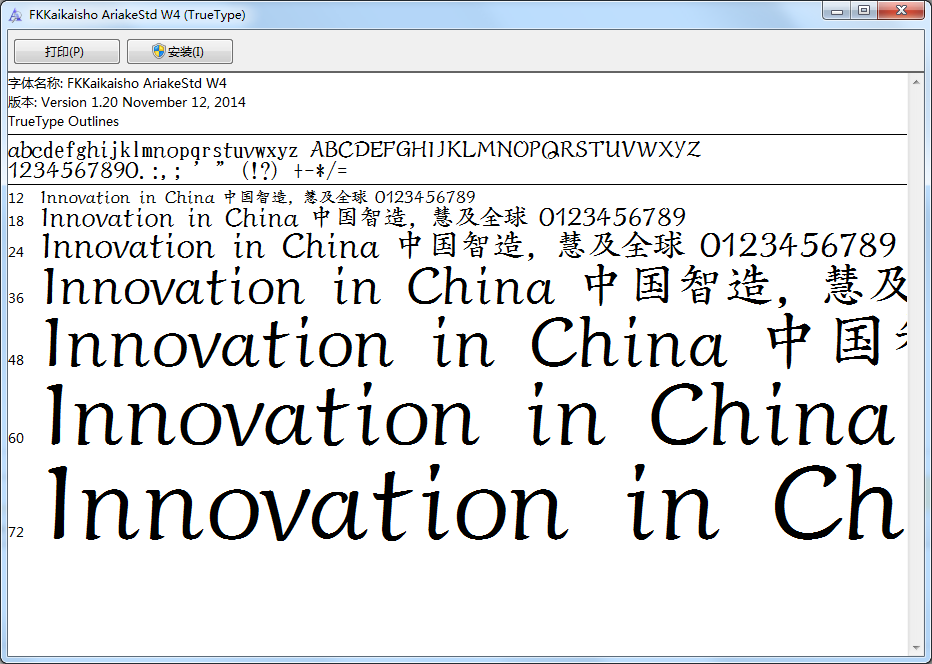
日本解楷書(shū)體字體是一款非常好看的字體,字體粗細(xì)適中,看著讓人覺(jué)得非常的清新自然,可廣泛使用,支持中文、英文和阿拉伯?dāng)?shù)字,喜愛(ài)的朋友趕快到綠色資源網(wǎng)下載使用吧!
日本解楷書(shū)體是一款用于楷體書(shū)法設(shè)計(jì)方面的字體,整體字形筆畫(huà)均衡,棱角分明,結(jié)體寬綽秀美外似柔潤(rùn)而內(nèi)實(shí)堅(jiān)強(qiáng),形體端秀而骨架勁挺,本作品適用于書(shū)體設(shè)計(jì)字體、平面設(shè)計(jì)字體、楷體設(shè)計(jì)字體。